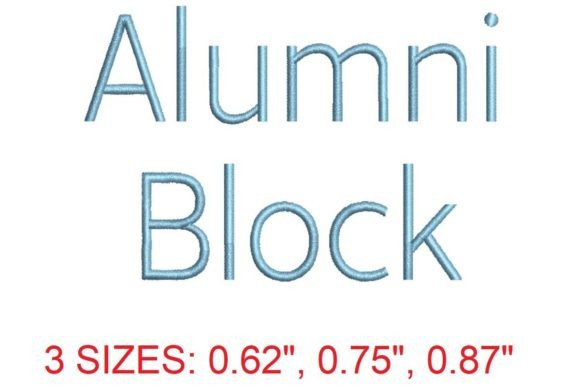
Alumni Block Embroidery Font
Het vinden van de juiste ontwerpelementen kan lastig zijn, maar Alumni Block Embroidery Font biedt een uitzonderlijke collectie die uw werk direct naar een hoger niveau tilt.
Met precisie gemaakt, biedt Alumni Block Embroidery Font strakke vectoren, vloeiende typografie en een commerciële licentie voor uw gemoedsrust.
Of u nu POD-producten (Print on Demand), huwelijksuitnodigingen of afbeeldingen voor sociale media maakt, Alumni Block Embroidery Font is een ideale keuze.